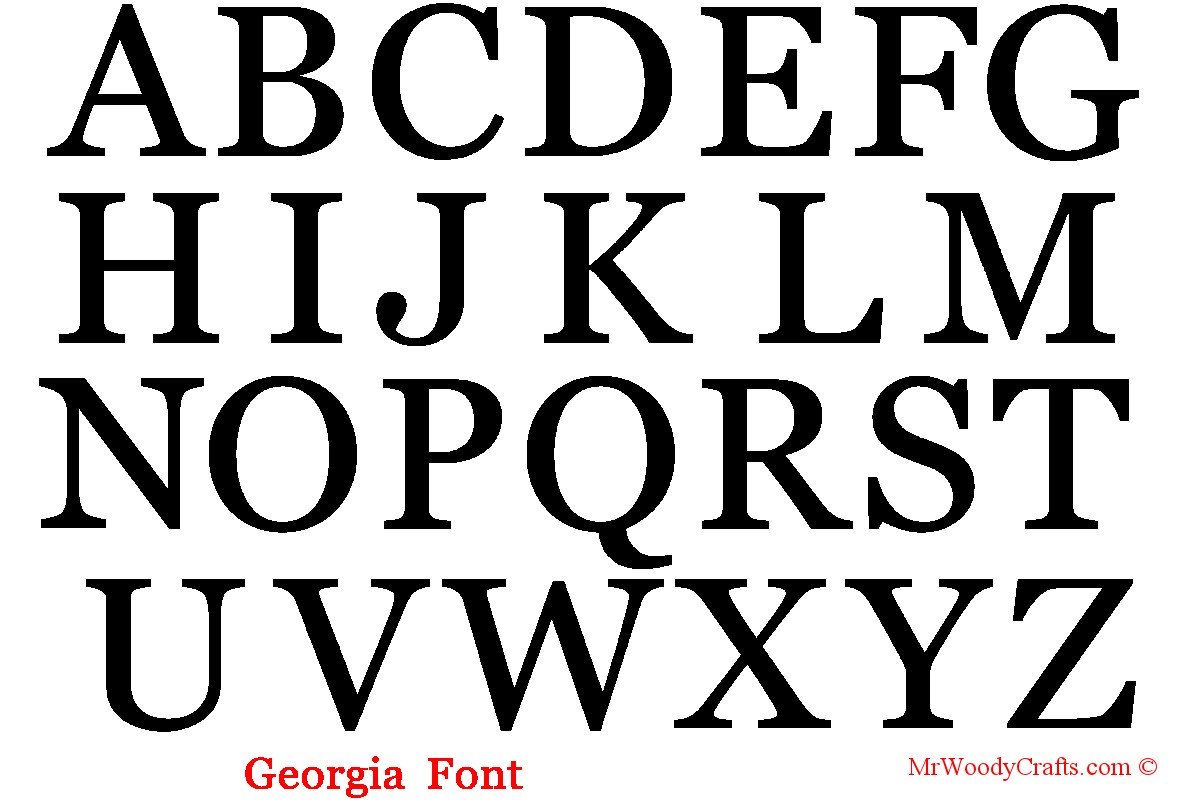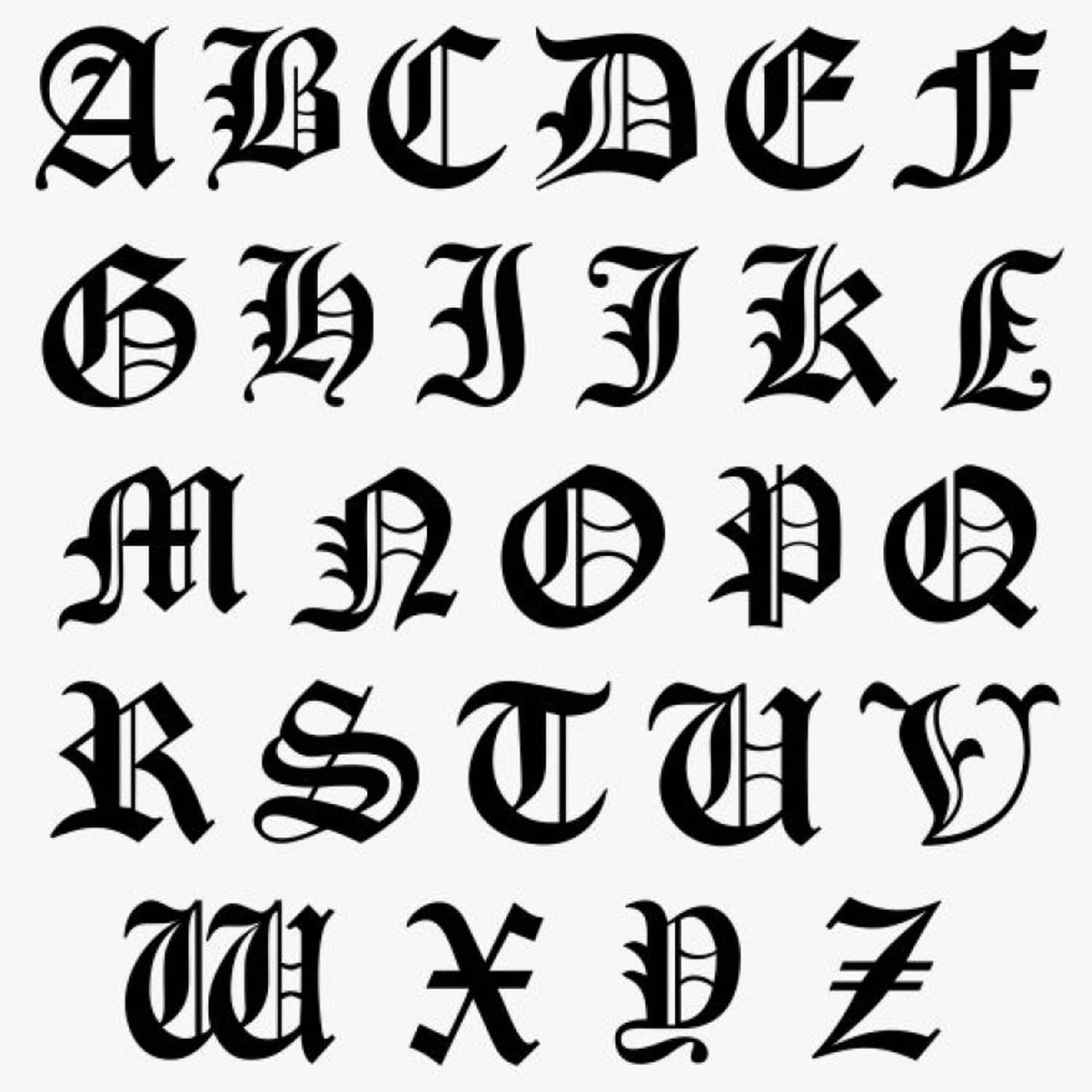
Творческий английский алфавит складной шрифт
Английский алфавит с названием букв, транскрипцией и произношением
В английском алфавите всего 26 букв, а в русском – целых 33.
Обычно одной согласной букве соответствует один звук, а вот букве X соответствует два звука – KS.
Британское и американское произношение немного различаются. Это касается буквы Z – британский вариант – [zed] “зед”, американский – [zi:] “зи”. Самые часто встречаемые буквы – это E и T (самое частое слово – the), а самые редкие буквы – Z и Q. Знание этого позволило Шерлоку Холмсу расшифровать письмо, где каждая буква была заменена на значок.
Как правильно произносить алфавит? Вот все буквы с английской и русской транскрипцией. Русская транскрипция приведена только для самых начинающих, а вообще надо учить английскую транскрипцию – без нее никуда, она используется во всех словарях.
Здесь вы можете выучить или повторить алфавит английского языка. Представлены все буквы английского языка, их название, рукописный шрифт и произношение.
Печатный шрифт | Рукописный шрифт | Название букв | Произношение |
Английский алфавит в готическом стиле.
Интересно, что готический стиль написания берет свое начало из греческого алфавита. В 300 г. до н.э. Александр Великий (Македонский) устанавливает греческий язык в качестве единого на огромной территории. Следующая Великая Империя – Римская, переняла удобную греческую письменность, но основным средством общения у римлян стал латинский язык с его прямым антиквенным шрифтом (здесь впервые появились засечки на заглавных буквах (капителях) – serifs). Латынь была заимствована у этрусков, буквы которых, в свою очередь, основывались на греческом алфавите.